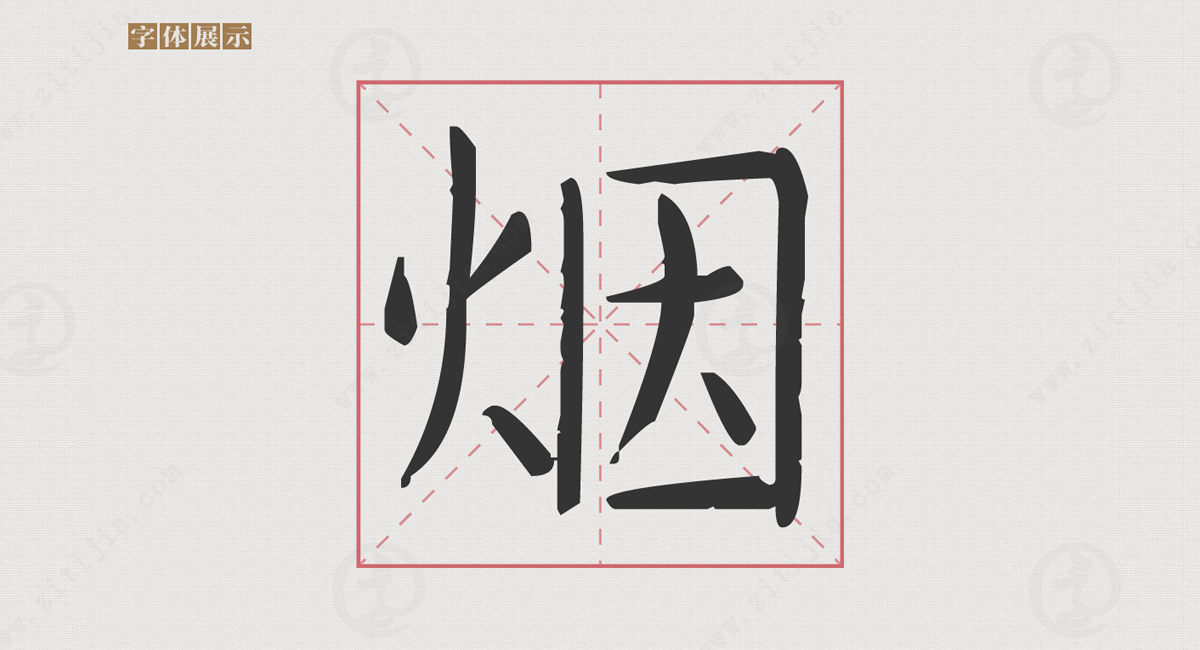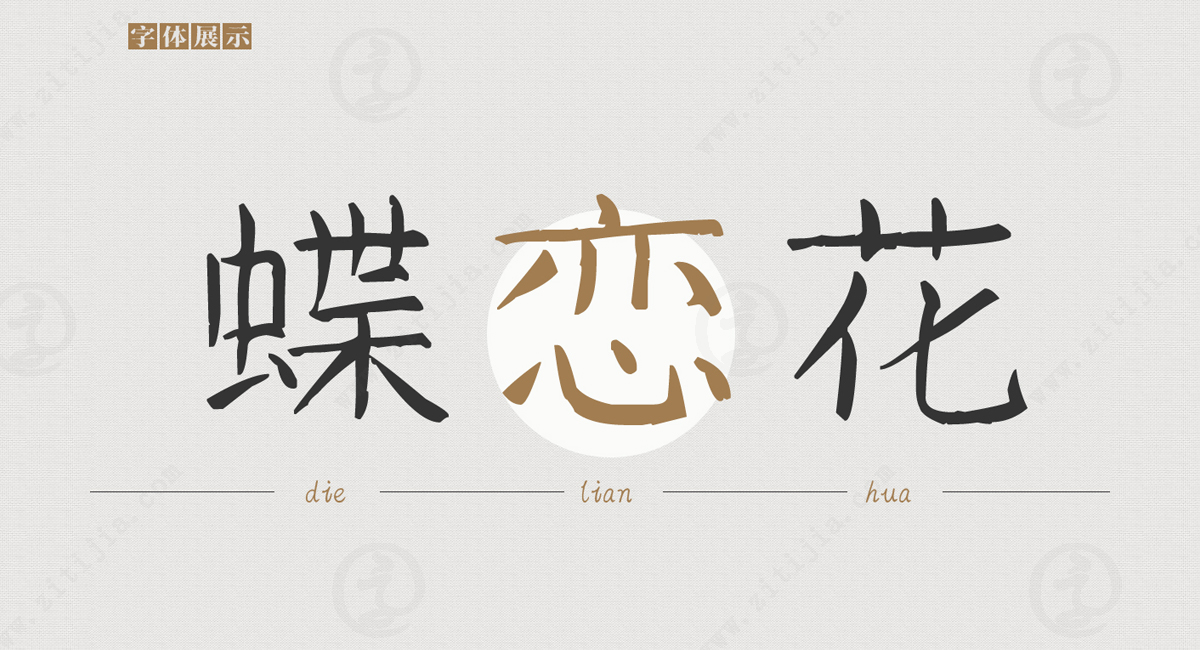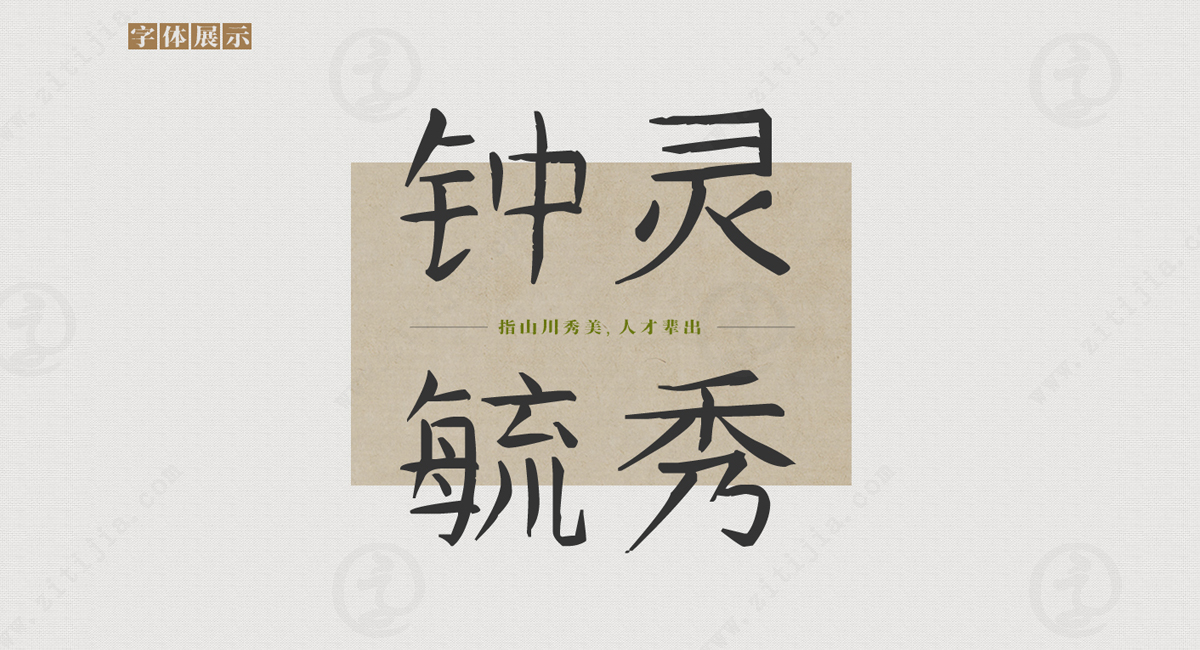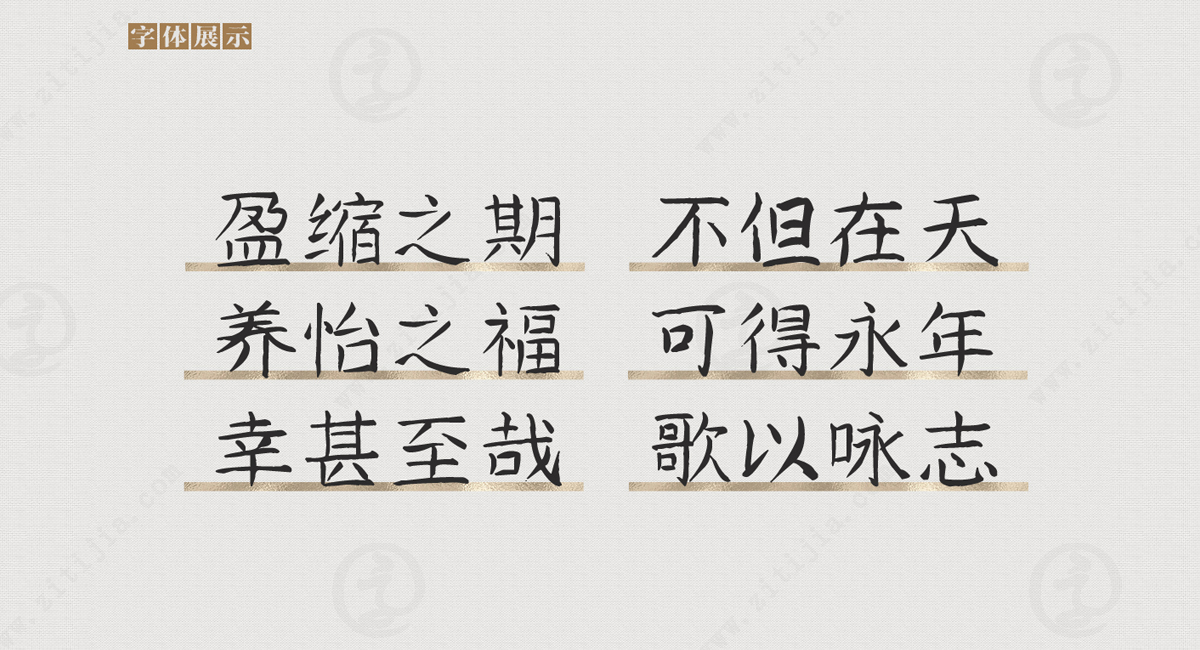
优美的楷书风格,南构迁词手写字体欣赏
南构迁词手写字体是一款非常优美的手写硬笔字体,它采用了楷书的风格,字形方正,非常清晰,容易识别。这款字体的笔画非常有力,线条流畅,让人感觉非常舒适。它的设计灵感来源于传统楷书,融合了现代设计元素,形成了一种独特而又典雅的风格。
南构迁词手写字体适用于各种场合,包括书法、印章、海报、广告、书籍封面等多种用途。在书法领域中,它可以用于书写碑帖、行书、楷书等多种字体风格,展现出不同的艺术魅力。无论是作为书法爱好者的练习字体,还是作为专业书法家的展示字体,南构迁词手写字体都能够展现出其独特的韵味和美感。
在印章设计中,南构迁词手写字体的方正字形和清晰线条使得印章的字体非常清晰可辨,给人一种庄重而又精致的感觉。无论是作为企业的公章、个人的名章,还是作为礼品、纪念品的印章,都能够通过南构迁词手写字体展现出高雅的品味和独特的个性。
在海报和广告设计中,南构迁词手写字体的优美特点可以使得文字更加生动有力,增加设计作品的艺术感和吸引力。它的线条流畅,字形方正,使得文字在海报和广告中非常醒目,能够吸引人们的注意力,传递出准确而又美观的信息。
此外,南构迁词手写字体还可以应用于书籍封面设计中。它的独特风格和优美字形可以使得书籍封面更加精美、独特,吸引读者的眼球。无论是文学作品、艺术书籍还是学术著作,南构迁词手写字体都能够为书籍增添一份艺术性和独特的魅力。
总之,南构迁词手写字体是一款优美的手写硬笔字体,它采用了楷书的风格,字形方正,非常清晰,容易识别。它的笔画有力,线条流畅,让人感觉非常舒适。无论是在书法、印章、海报、广告还是书籍封面等多种用途中,南构迁词手写字体都能够使得设计更加精美、独特,具有艺术性。它的出现丰富了字体的选择,为设计师和艺术爱好者提供了一种全新的表达方式。无论是在传统领域还是现代设计中,南构迁词手写字体都能够展现出其独特的魅力,成为设计作品中不可或缺的一部分。